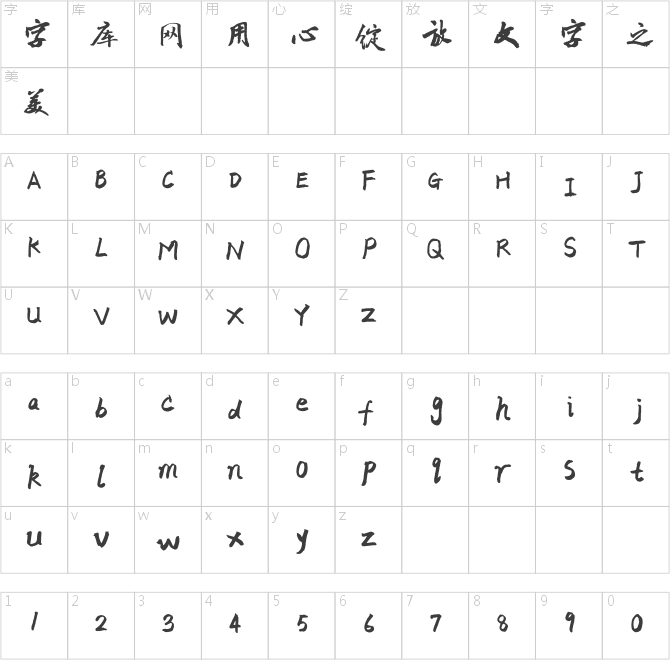
字体名称: 桃煦古风广告简
《桃煦古风广告简体》是一款适合视频制作、平台设计和办公文稿的毛笔字体。该字体适全当今 时代阅读和审美要求,在学习和传承中国书法,充分发挥电脑等现代信息技术优势,将古风古韵融入现代广告字体,整理形成的一套适应视频制作、平面设计和电脑方案起草的字体。主要特色如下:
一、具有古风古韵。充分汲取中国5000多年书法丰富的营养,尽力展现古人笔法、结字和墨色,发挥毛笔丰富的点画、线条表现特色,使字体具体较强的古风古韵。
二、适应现代审美。紧跟当今时代时代发展趋势,适应现代信息对广告、美术等字体的需求,注重使用简体字规范字,避免个别读者辨认繁体字费时,日渐生疏的困惑。
三、较强使用场景。不仅是电脑上视频制作、平台设计和文稿处理的PC字库,而可适用于手机和平版等电子产品,能够在多种场景使用和运用。
桃煦古风广告简体字体桃煦古风广告简体字库是一款让人赏心悦目、百看不厌的中文字体,适合各类广告和产品包装设计应用,字体大小5.28MB,格式为otf字体,上传用户是激流一叶,作者/版权方为陶旭